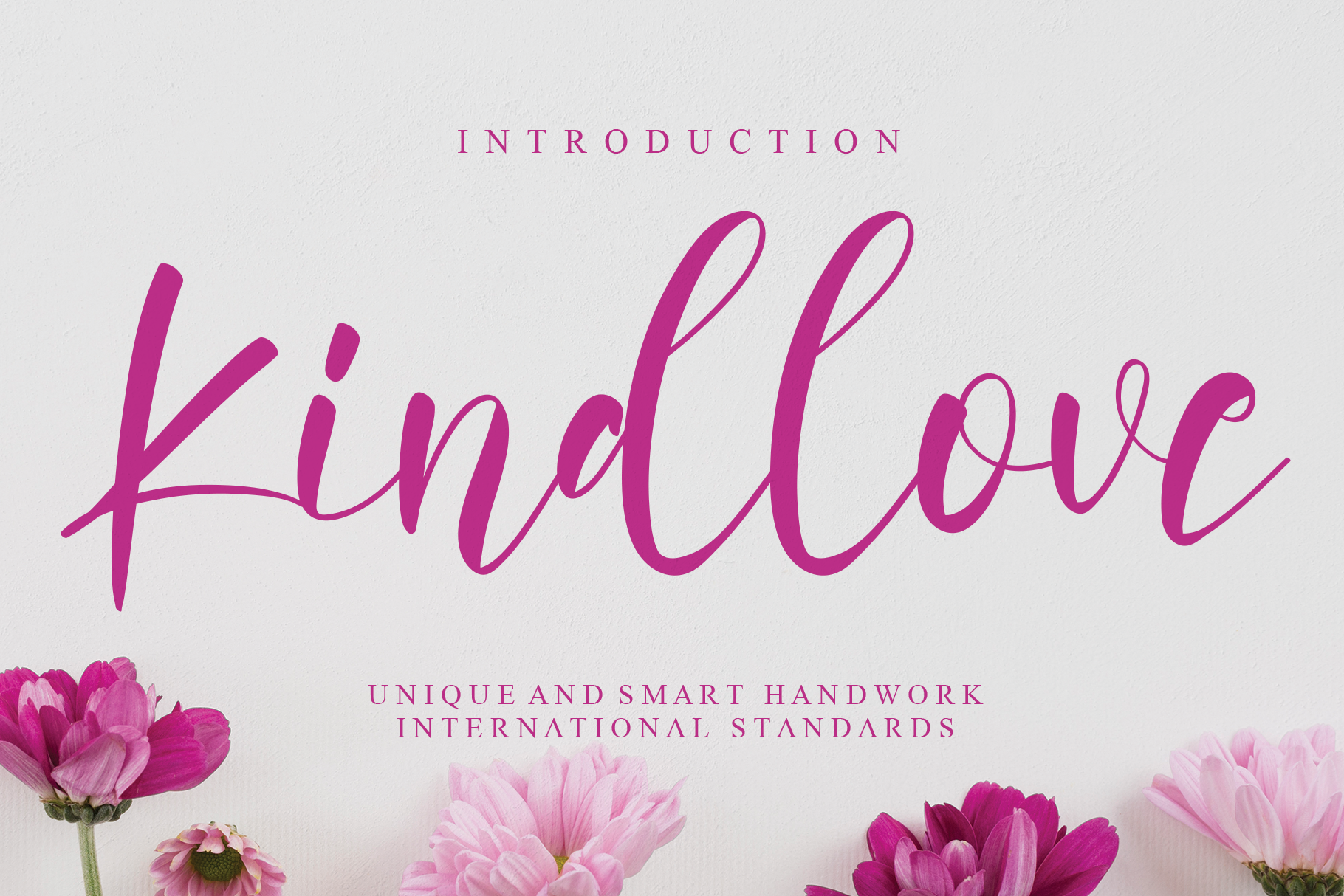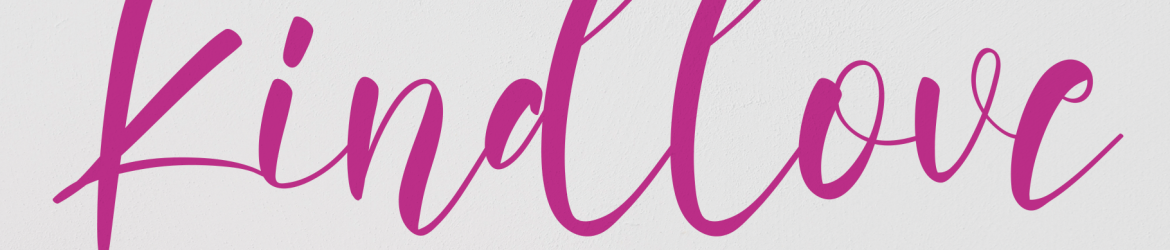
Kindlove Font – Download Grátis
Esta é uma fonte de escrita manuscrita encantadora. Ela oferece um estilo completamente único que permanece eterno, tornando-a perfeita para quem busca uma fonte ideal para criar designs impressionantes. Se você a usar com o ‘Kindlove Font’, certamente sentirá a energia do amor ao olhar nos traços elegantes e surpreendentes. Perfecto para designers em busca de um toque autêntico que vai destacar seus projetos gráficos. CriativeLetter é conhecido por suas fontes de escrita manuscrita cheias de vida, e esta certamente não é uma exceção.